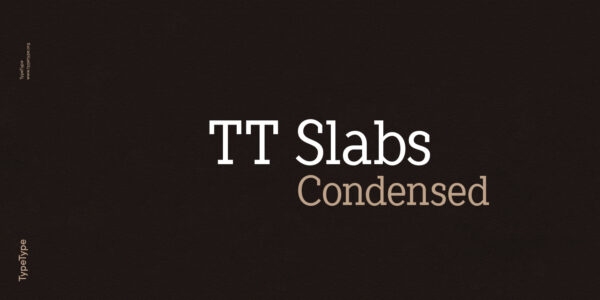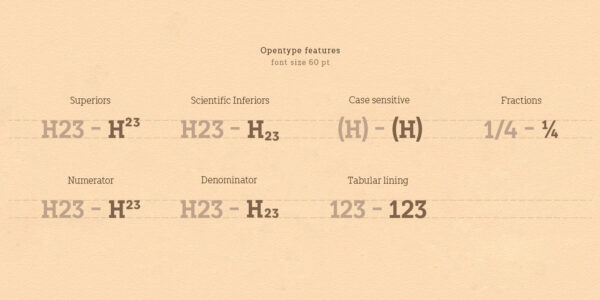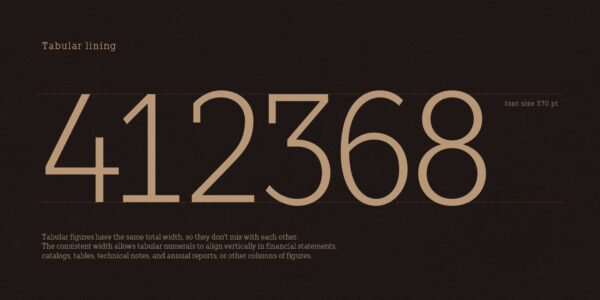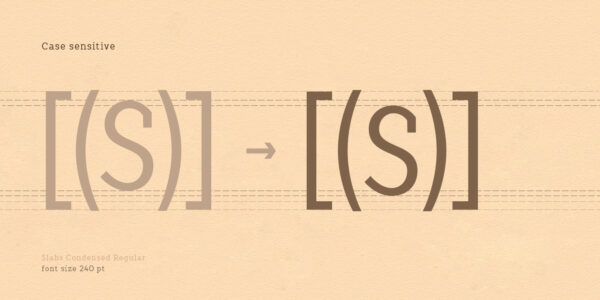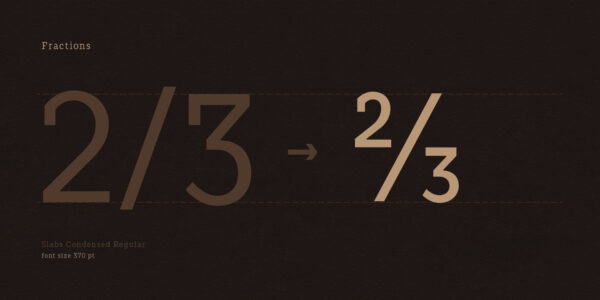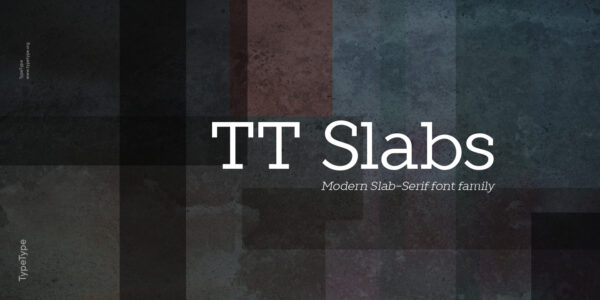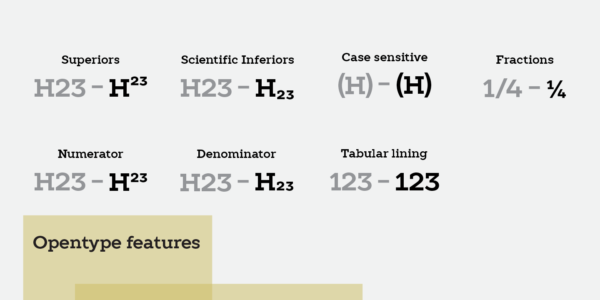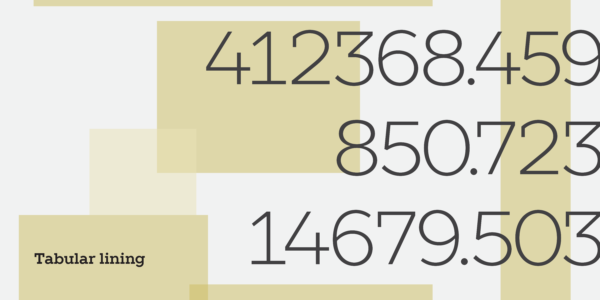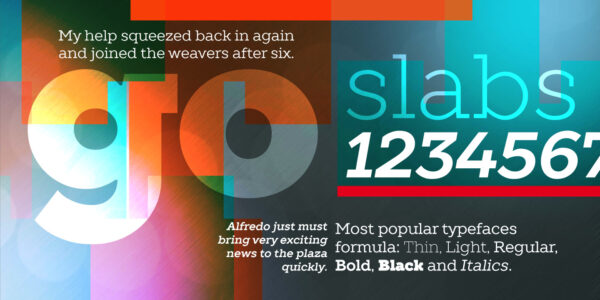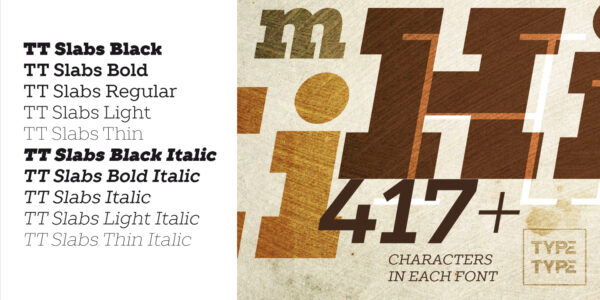
TT Slabs
TT Slabs — ТТ Слабс
Произносится «ТТ Слабс». «Slabs» — производное слово от slab, в переводе с английского «слаб, брусковый шрифт». Буквы «TT» являются аббревиатурой названия компании
TT Slabs — универсальный брусковый шрифт с лаконичным рисунком и широкими пропорциями.
Универсальный шрифт с широкими пропорциями
Мир нуждается в красивых, простых и высококачественных шрифтах. TT Slabs является простой и геометричной брусковой гарнитурой. TT Slabs включает в себя классическую формулу начертаний.
TT Slabs подойдет дизайнерам, которые занимаются брендингом и айдентикой, логотипами
А также для дизайна интерьера и навигации
О гарнитуре TT Slabs
Мир нуждается в красивых, простых и высококачественных шрифтах. TT Slabs является простой и геометричной брусковой гарнитурой. TT Slabs отлично подойдет вам, если для ваших проектов вы ищете универсальный шрифт с широкими пропорциями.
case | Case Sensitive Forms
frac | Fractions
numr | Numerators
dnom | Denomerators